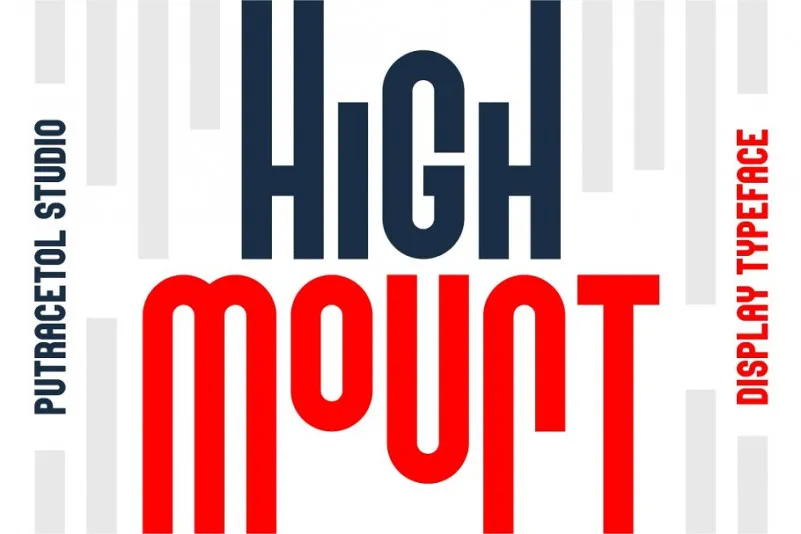
High Mount Typeface
A High Mount Typeface é uma nova tipografia projetada para ambientes de exibição de grande porte, ideal tanto para headlines quanto títulos grandiosos. Esta fonte foi criada especificamente para dar destaque e expressar sua mensagem com clareza nos grandes espaços visuais. Conhecida por seu desempenho excepcional nas logo design, branding e etiquetas, a High Mount Typeface é uma escolha ideal para um amplo espectro de aplicativos gráficos. Suas três alturas diferentes — normal, média, alta e muito alta — permitem que você crie um visual único e versátil, adaptável a diversos usos como logomarcas, roupas personalizadas, cartões de apelo, embalagens, mensagens em destaque e mais. Ideal para capturar a atenção do público em grandes mídias sociais, cartazes, produtos ou até mesmo cartões de visita. Seja você um designer gráfico ou criador de conteúdo digital, High Mount Typeface é uma opção excepcional que pode adicionar profundidade e estilo ao seu trabalho.